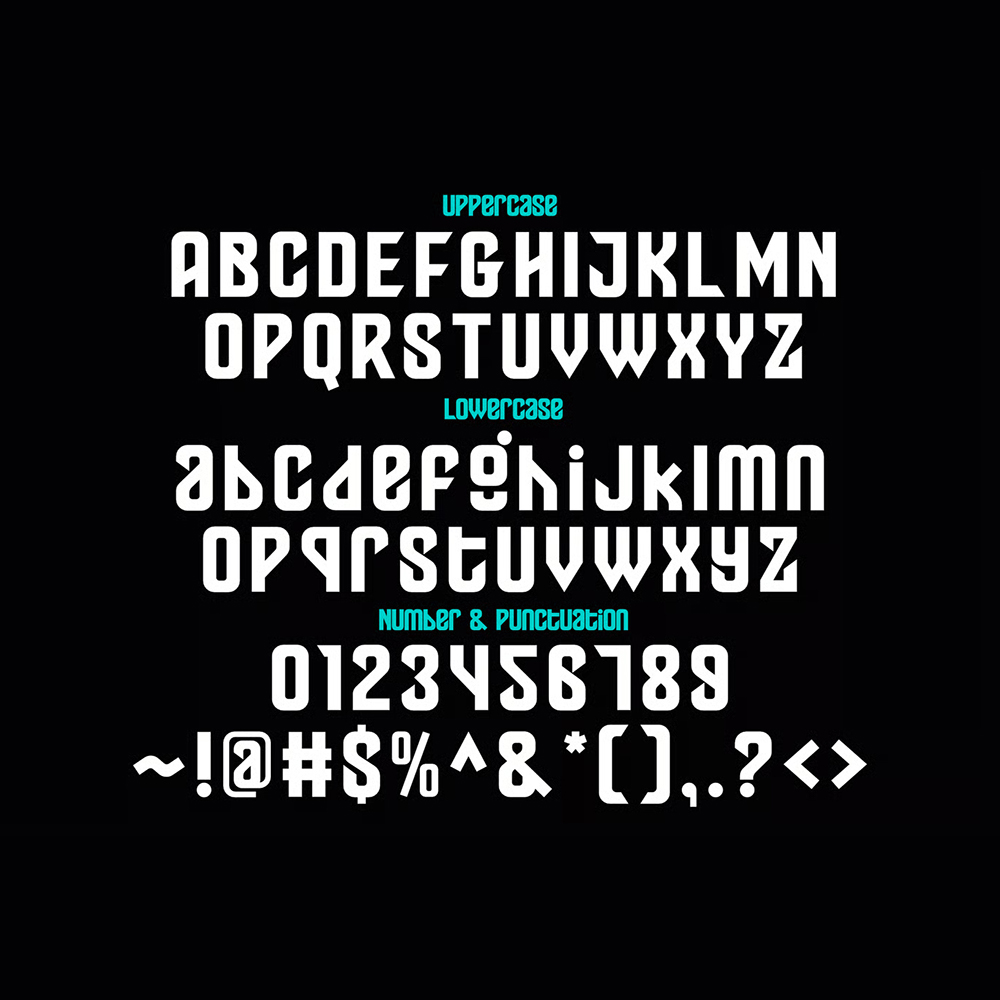
دانلود فونت انگلیسی Jagot Font
فونت پرمیوم و انگلیسی Jagot یک فونت مدرن و همهکاره است که برای برندسازی معاصر طراحی شده است. این فونت با خطوط تمیز و تناسبات متعادل، برای ایجاد لوگوها، تیترها و طرحهای سرمقالهای تأثیرگذار ایدهآل است. سبک مینیمالیستی آن، خوانایی را در عین ظرافت تضمین میکند.
مزایای استفاده از فونت لاتین Jagot Font چیست؟